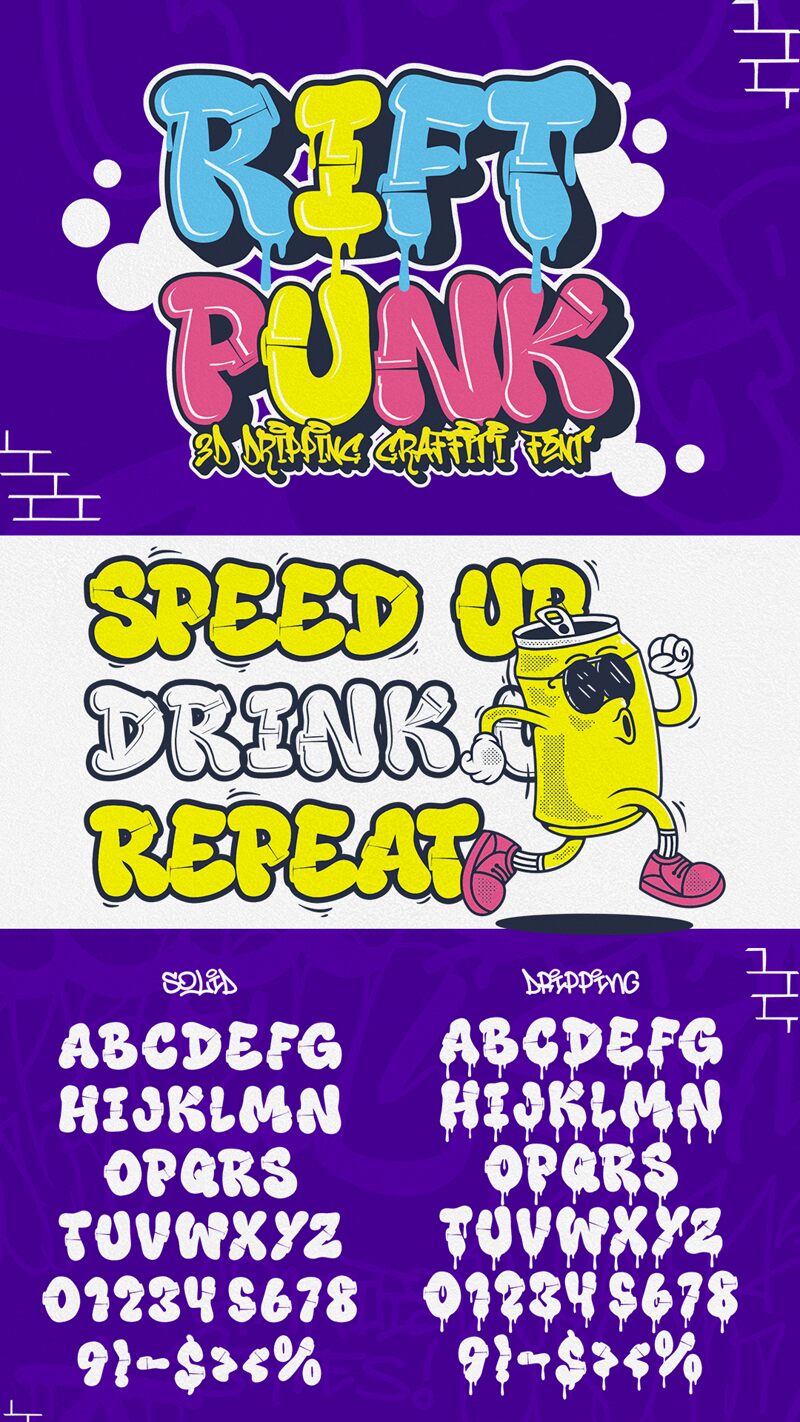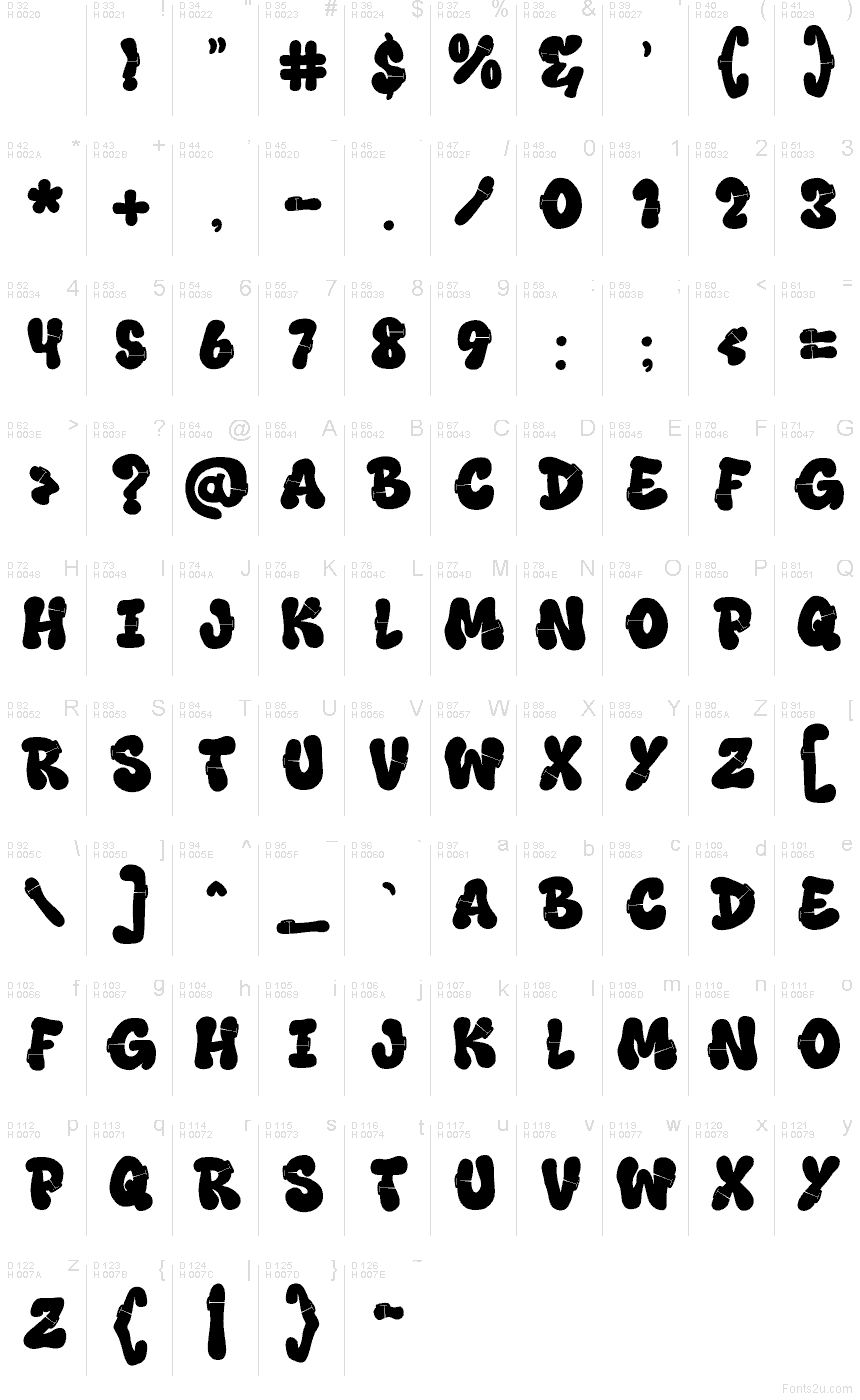
Rift Punk Solid Solid
Il font Rift Punk Solid di Muhammad Panji Ramdhani, della fonderia Cikareotype, è un carattere graffiti gratuito che fa parte della famiglia Rift Punk. È caratterizzato da tratti spessi e gommosi e da bordi irregolari che ricordano la vernice fresca su un muro di mattoni. Le lettere sono audaci e compatte, rendendo il messaggio di grande impatto fin dal primo sguardo, con un ritmo punk giocoso.
Con Rift Punk Solid otterrai risultati incisivi su loghi streetwear, brand di skateboard o sneakers, flyer musicali, titoli di poster, adesivi, miniature di YouTube e copertine di album o mixtape. Usa Rift Punk Solid in grandi dimensioni e lascia che respiri; abbinalo a un carattere sans serif condensato e pulito per date, crediti o testo piccolo, per mantenere la leggibilità all'interno del caos creativo di questo font gratuito.